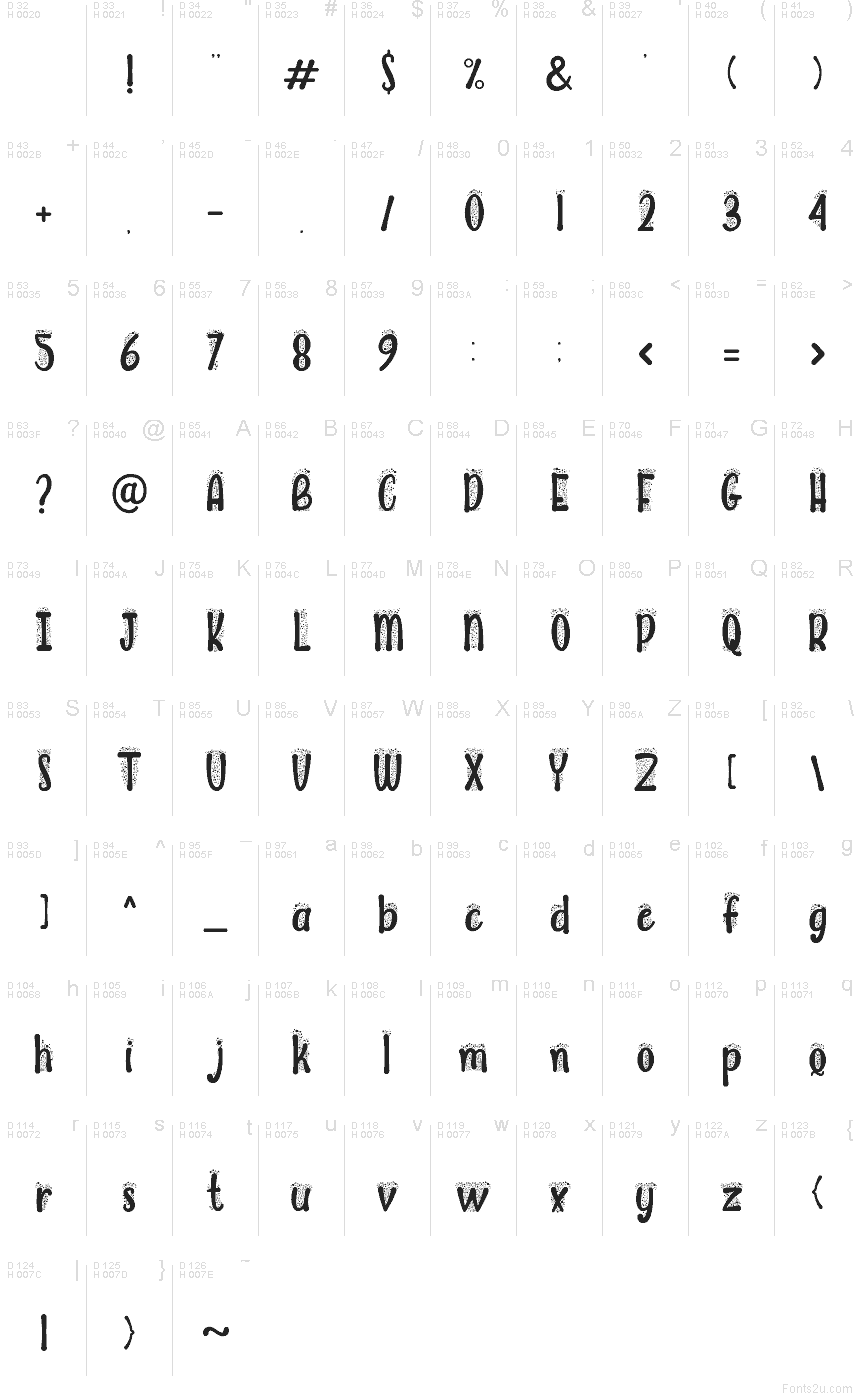
Cute Snow Snow Drop von Putracetol Studio ist eine kostenlose, weihnachtliche Script-Schrift mit einem verspielten, handgezeichneten Look, deren Buchstaben mit fallenden Schneeflocken bedeckt sind. Die weichen, geschwungenen Formen und die verstreuten Punkte verleihen dieser Schrift eine winterliche Märchenstimmung, die fröhlich und ungezwungen wirkt.
Sie passt perfekt auf Weihnachtskarten, Geschenkanhänger, Verpackungen für Backwaren, Partyeinladungen und saisonale Social-Media-Posts, bei denen die verschneite Textur die Gestaltung übernimmt. Als kostenlose Schrift eignet sie sich ideal für kurze Überschriften, Cover-Texte und Titel, die einen leichten, festlichen Touch brauchen, ohne den lebendigen Charme der Buchstaben zu verlieren.